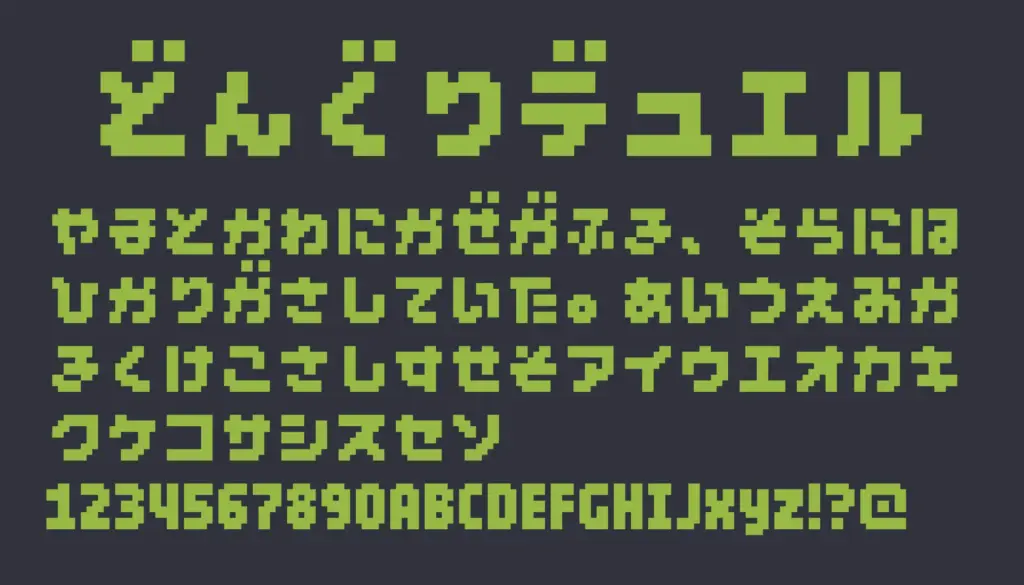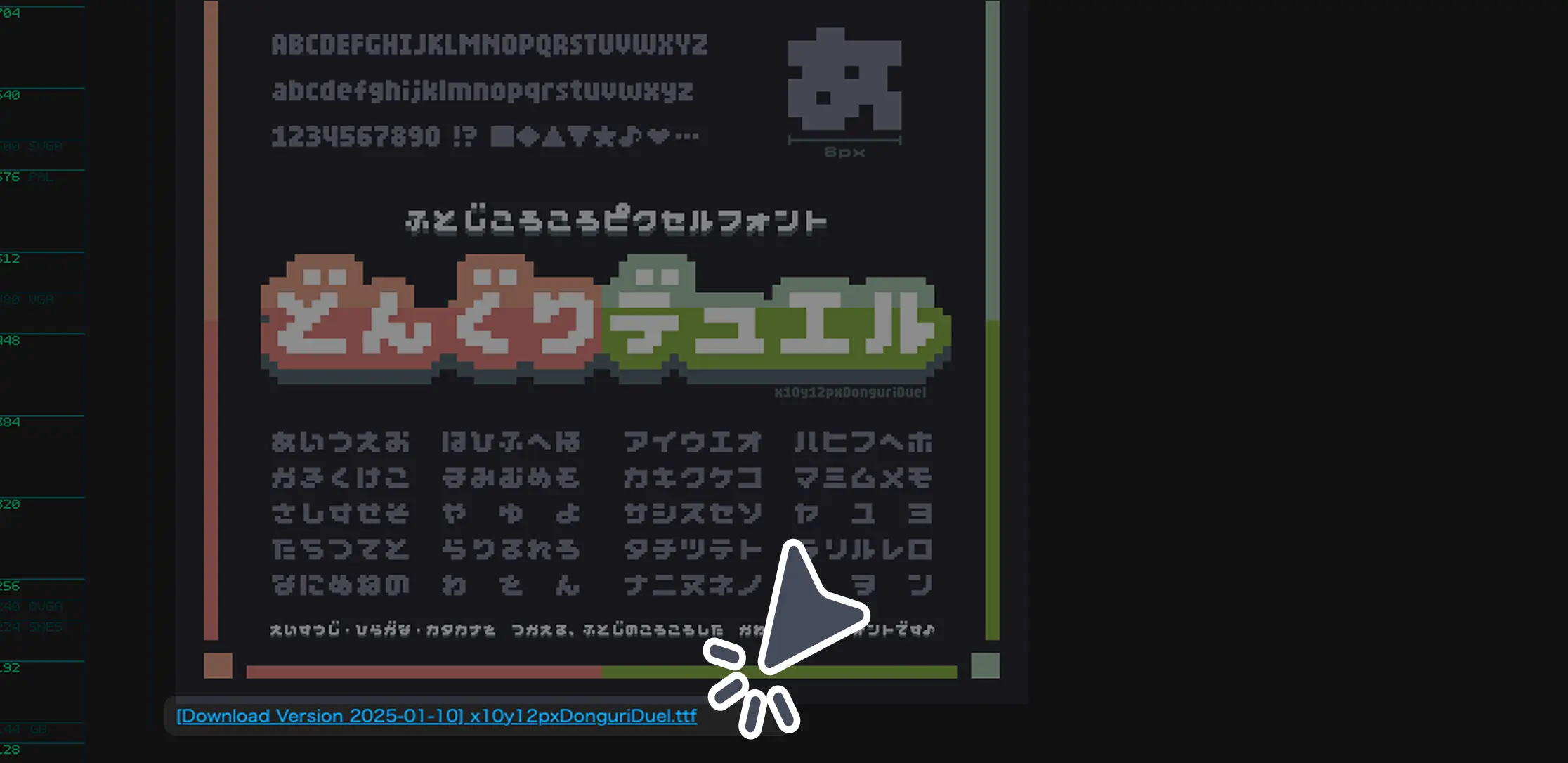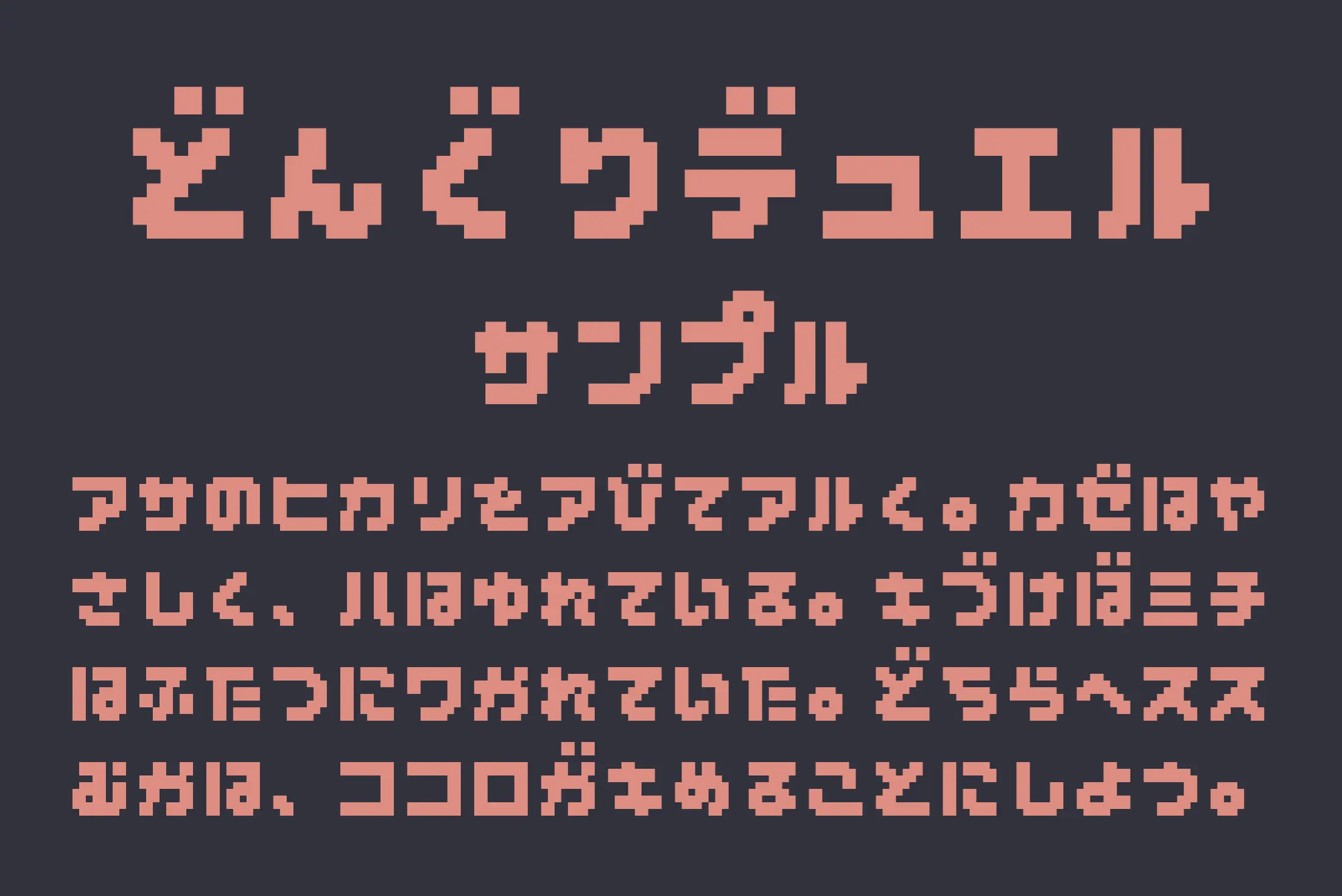
太めでころんとしたフォルムが特徴的なドット(ピクセル)フォントです。10×12 ピクセルサイズで設計されており、レトロゲームを思わせる8ビット感を活かしつつ、丸みを帯びた丸ゴシック風の親しみやすさも兼ね備えています。ゲームタイトル、動画サムネイル、レトロデザインの UI にぴったり。商用利用も可能なのが嬉しいポイントです。
どんぐりデュエル